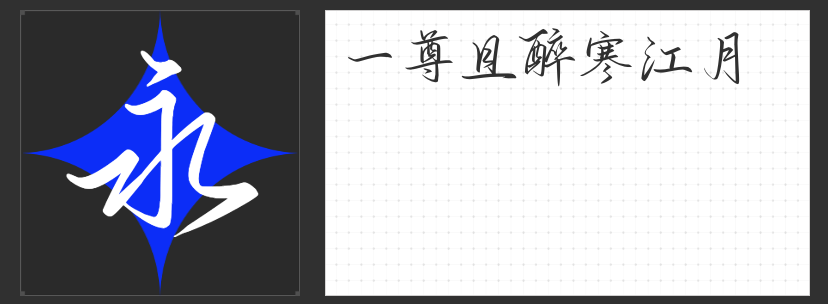
国潮设计中的字体新贵:四款传神书法字库推荐
在国潮设计浪潮中,书法字体始终是传递东方美学精神的核心载体。以下四款兼具艺术张力与文化底蕴的收费字体,以独特的笔墨语言诠释了传统与现代的融合之道,为品牌视觉注入刚柔并济的侠骨风韵。
一、造字侠伏魔简繁·传神
这款字体以刀刻斧凿般的笔触重构汉字骨架,粗细对比达1:3的强烈反差形成视觉锚点。其"勾、挑、捺"等笔画末端的夸张飞白,既保留了碑刻的苍劲质感,又通过中宫收紧、外围舒展的结构处理,使单字在密集排版时仍保持呼吸感。特别适合作为主标题字体,在茶器包装、武侠游戏界面等场景中营造出"一剑破空"的震撼效果。
二、造字侠仗剑简繁·传神
设计师从明代剑谱插画中汲取灵感,将折笔处理为45度锐角转折,提钩部位采用双重顿笔技法,形成类似剑刃反光的金属质感。笔画间留白的精准控制,使文字在快速阅读时仍能保持辨识度。这款字体尤其适合运动品牌、国风音乐节的视觉系统,其动态平衡感完美诠释了"静如处子,动若脱兔"的东方哲学。
三、造字侠侠义简繁
突破传统草书的恣意放纵,通过计算机辅助设计重构笔画连结逻辑。圆转弧线占比达65%的独特设计,使文字如行云流水般自然衔接,而勾挑牵丝的数字化优化,既保留了书法笔意,又确保了小字号下的可读性。在高端白酒包装、文化纪录片字幕等场景中,这款字体能完美演绎"大巧若拙"的东方美学境界。
四、字圈也字醉寒江行草
取法文徵明小楷的骨法用笔,融入行草的流动韵律,通过0.8mm极细笔触与3.5mm粗笔的对比,构建出独特的"冰雪纹理"。收笔处的枯墨处理与起笔的蓄势待发形成微妙呼应,如同墨汁在宣纸上自然晕染。这款字体在香道产品、禅意空间导视系统等场景中,能营造出"寒江独钓"的意境空间。
这四款字体通过数字化技术重新解构传统书法,既保留了笔墨纸砚的物理特性,又突破了媒介限制。为国潮设计提供了更具文化深度的视觉解决方案。